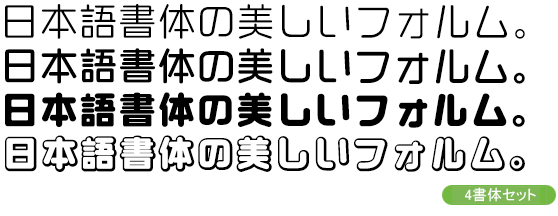
まーと3書体+オープンタイプ
丸ゴシックなのに、直線を意識したフォルムでオリジナリティを追求しました。まーと3書体(中細丸/中丸/太丸)+ まーとオープンボールドの4書体セット。
CFONTは下島正人氏が手掛けるフォントライブラリー。キャッチコピーやタイトルを目的としたディスプレイタイプフォントを制作しており、個性的なフォルムを重視しながらも可読性も考慮されたデザインが特徴です。